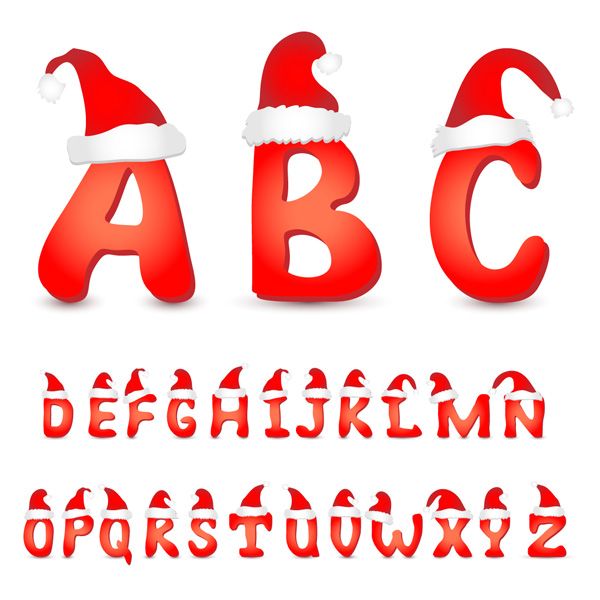
Бесплатные новогодние шрифты — как сделать красивый логотип к праздникам
Новогодние шрифты — это декоративная типография, которая используется в сезон зимних праздников, чтобы украсить контент и создать соответствующее настроение бренду.
Праздничные шрифты применяются для временного оформления веб ресурсов, элементов фирменного стиля, логотипов, емейл рассылки, открытки и т.д. Таким образом компания может продемонстрировать свою гибкость к внешним факторам и заботу к целевой аудитории.
Ярким примером создания новогодней атмосферы благодаря стилизации бренда является логотип Coca Cola.
Шрифты, которые отлично украсят ваш логотип к праздникам
Если вы также хотите украсить свой бренд к праздникам, тогда начните именно со шрифтов. Возможно, это единственное, что нужно поменять, чтобы фирменный стиль заиграл по-новогоднему. Поэтому давайте познакомимся с некоторыми примерами декоративных шрифтов и их особенностями.
Candy Cane
Новогодняя пора — это всегда вкусно и сытно. Шрифт Candy Cane выглядит, как рождественские леденцы благодаря полосатому дизайну. Отсутствие засечек в шрифте делает его читабельным, текст смотрится опрятно и празднично одновременно. Сделайте свой текст “вкусным” для клиентов.
Kindly Jasmine
Ожидание сказки под Новый Год усиливается как у детей, так и у взрослых. Kindly Jasmine создала одноименный шрифт, дизайн которого напоминает бренд сказок Disney.
Marlyana
Вот еще немного сказочного дизайна в типографии. Алфавит с завитушками сделает праздничными заголовки вашего контента. Этот красивый шрифт относительно новый, художник Yuri Sinatra разработал его в 2018 году, но он уже успел привлечь к себе внимание.
Hanging letters
А вы уже думали чем украсить свою елку? Для этого подходит любая игрушка или конфета подвязанная на ниточке. А как вам подвязанные на ниточке буквы? В 2014 году дизайнер Hareesh Seela создал именно такой шрифт. Hanging Letters несомненно привлекает к себе внимание.
SnowCapCyr
Массивный шрифт без засечек смотрится не так уж и строго, под грудками пушистого снега. Типографический дизайн существует с 1990 года и уже набрал большую группу фанатов. Доступен как в латинке, так и в крилличном вариантах.
Hultog Snowdrift
Под Новый Год особо празднично выглядят присыпанные снегом дома и улицы.
А как насчет притрушенной снегом типографии? Ненавязчивая зимняя декорация создает нужное настроение, но при этом не мешает опрятности и читабельности текста.
PC Snowballs
Вы любили лепить снеговиков в детстве? А буквы алфавита? Да, такое тоже бывает. И для этого не нужно быть ребенком. Ведь шрифт PC Snowballs выглядит так, как будто он слеплен из снега. И вы можете слепить свой привлекающий контент, пользуясь им.
Eutemia I Italic
Зимние заверюхи свистят и пробирают до косточек. Но представляли ли вы когда-либо как они выглядят? В любом случае, взгляните еще разок. Ведь Eutemia I Italic со своими завитушками очень напоминает настоящую снежную заверюху. Красиво и символично — то, что нужно для новогодней декорации контента.
Hello Stockholm
Hello Stockholm универсален. Он не стилизован рождественскими деталями, поэтому может использоваться в любой сезон. Но что-то новогоднее в нем все же есть. Рукописный шрифт как будто создан для того, чтобы написать письмо Деду Морозу, но писать мы будем не ему, а любимым клиентам.
Christmas Eve
Что ассоциируется вам с зимними праздниками? Елка, новогодние игрушки и огоньки, снежинки, свечи, шапка Санты, подарки, леденцы или остролист — что же выбрать для декора рождественского шрифта? Vanessa Bays решила не выбирать и декорировала простой шрифт без засечек Christmas Eve всеми этими новогодними деталями.
Kingthings Christmas
Эти буквы с засечками, словно дети, играющие в снегу, делают шрифт особо привлекательным в зимний сезон. Kevin King декорировал Kingthings Christmas снежными сугробами и падающими снежинками. С 2009 года шрифт успел влюбить в себя не одну сотню дизайнеров.
Christmas Lights Outdoor
Раз, два, три — елочка гори! Но с Christmas Lights Outdoor сиять будет не елка, а ваш контент. В 2000 году Rich Gast создал действительно новогодний шрифт. Буквы обрамлены в иконки, напоминающие новогодние огоньки, создают действительно праздничную атмосферу.
Как украсить ваш логотип к Новому Году с помощью Adobe Photoshop
Новогоднего настроения не бывает много.
И если с текстом мы уже разобрались, то пришла пора взяться за логотип. Много компаний добавляют тематические детали на свои лого, чтобы создать актуальный вид корпоративному стилю к праздникам. Поэтому старый-добрый друг дизайнера — фотошоп к Новому Году довольно востребован. Давайте разберемся как оформить фирменный знак в новогоднем стиле, пользуясь Adobe Photoshop.